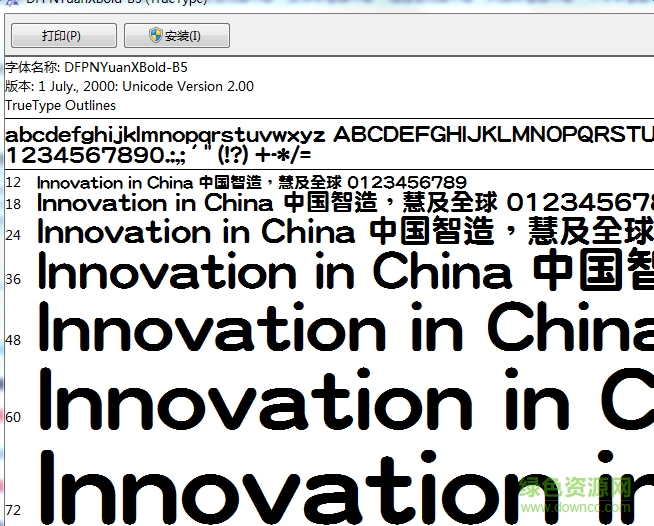
華康新特圓體字體是一款專門為藝術(shù)設(shè)計師們打造的新特圓體簡體字體,采用圓潤字型打造而成,您還在等什么?喜歡就來綠色資源網(wǎng)下載體驗唄!
這是一套設(shè)計師依多年從事廣告工作經(jīng)驗所開發(fā)出來的廣告專用字型,刻意的安排使整套字型效果與形象十分明確,令人一見難忘,而其中和的外形色彩,也使它在使用領(lǐng)域上十分廣泛。